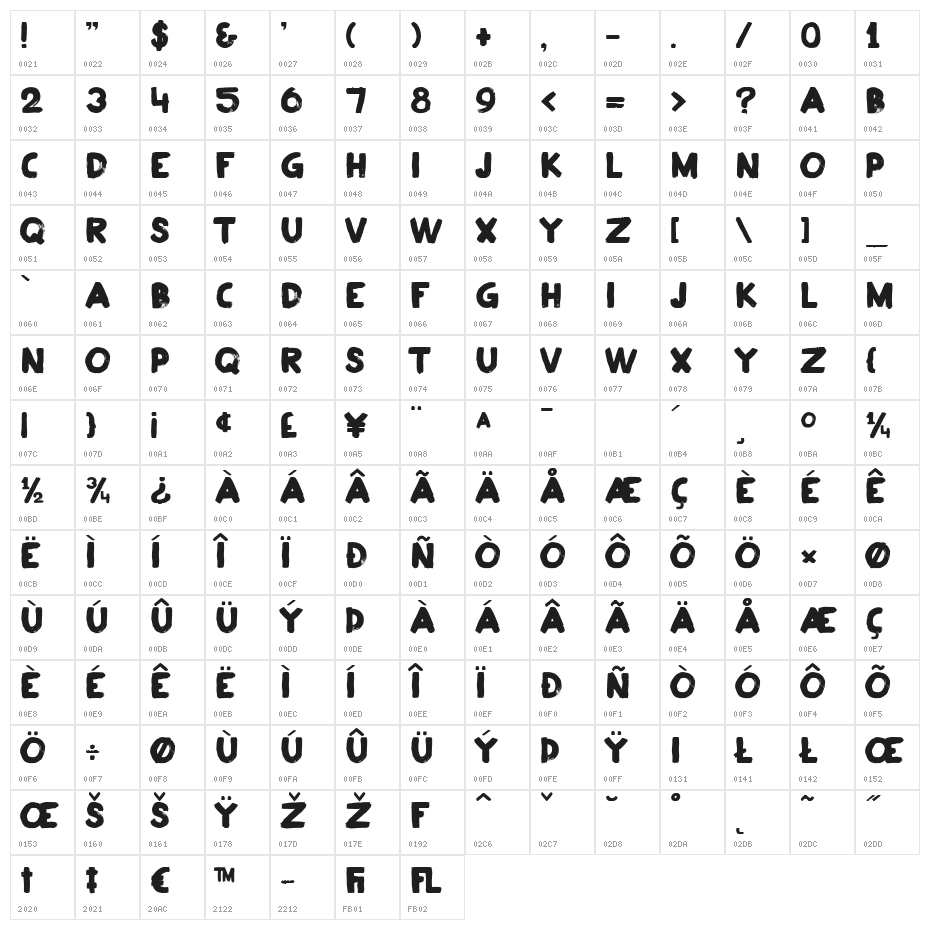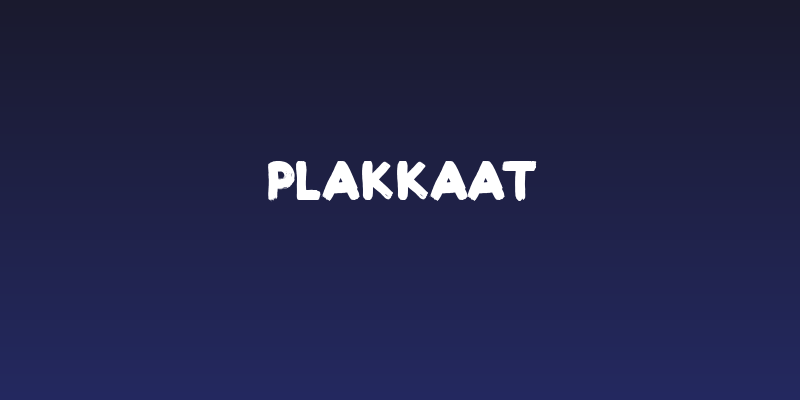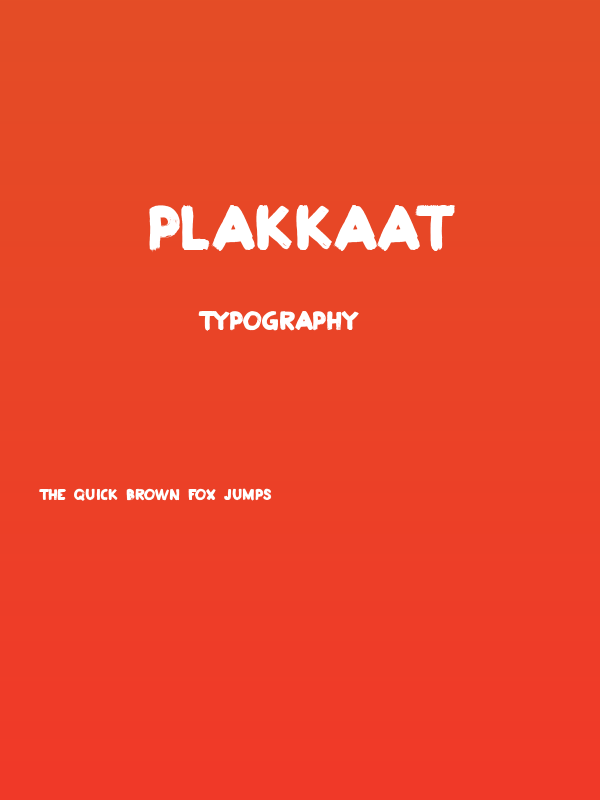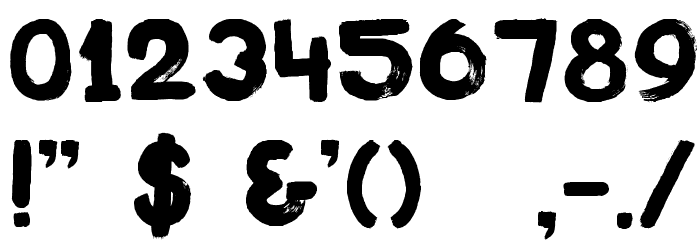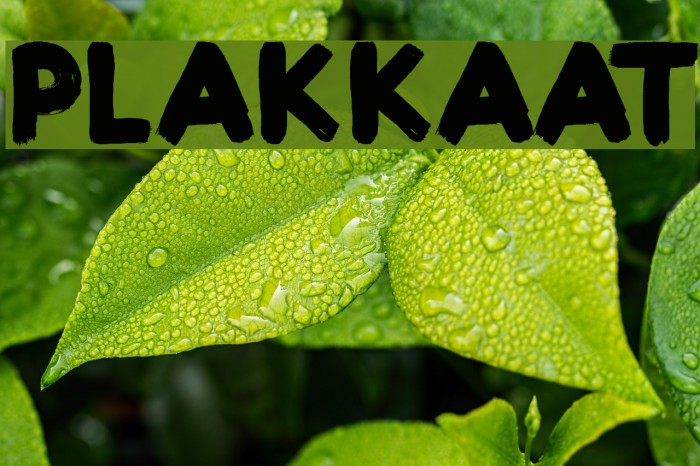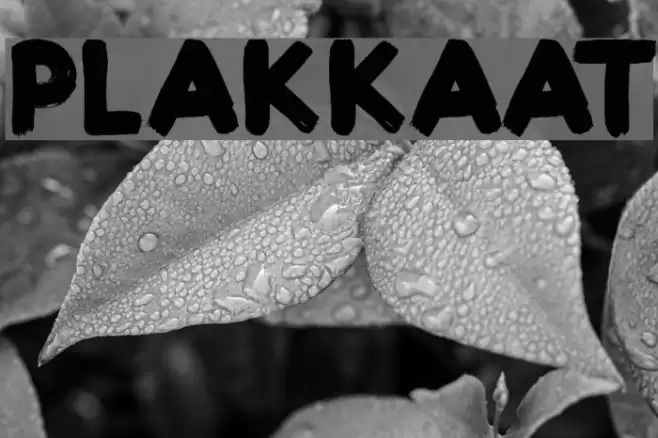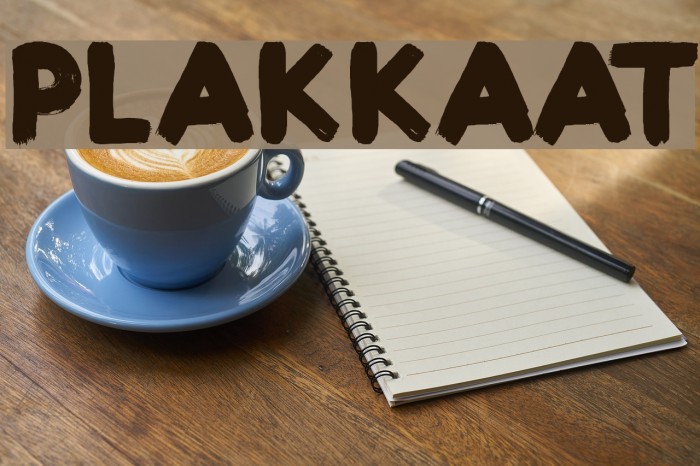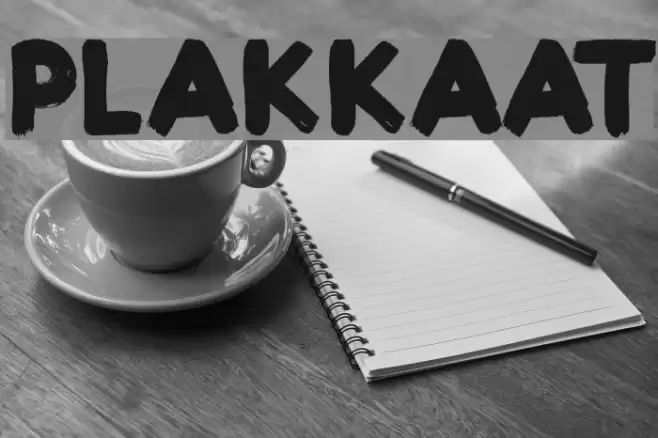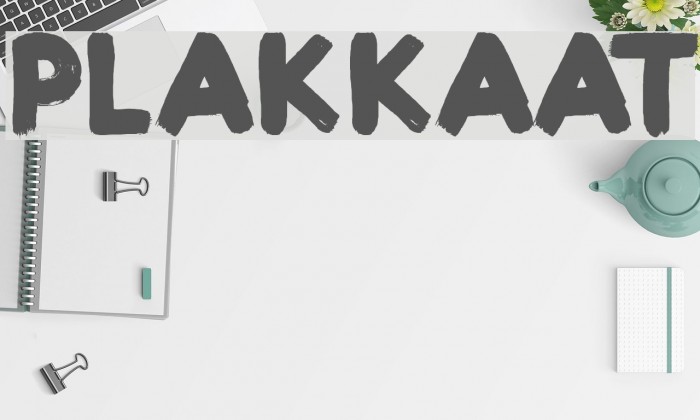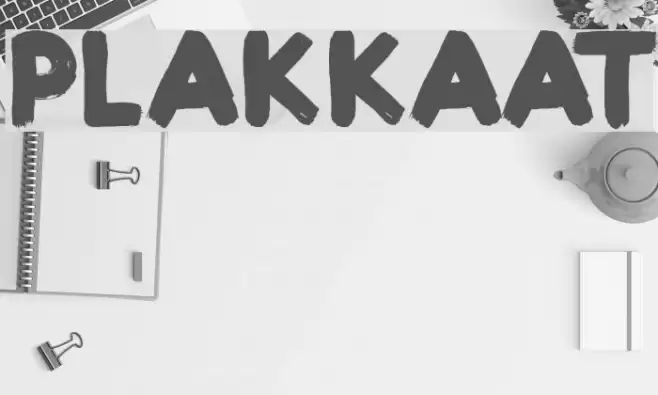
Plakkaat Font
✎ Messy
| Caso de uso | Headlines, Posters, Branding |
| Projetos propostos | Ideal for posters, branding, headlines, and artistic projects that require a bold, expressive typeface. |